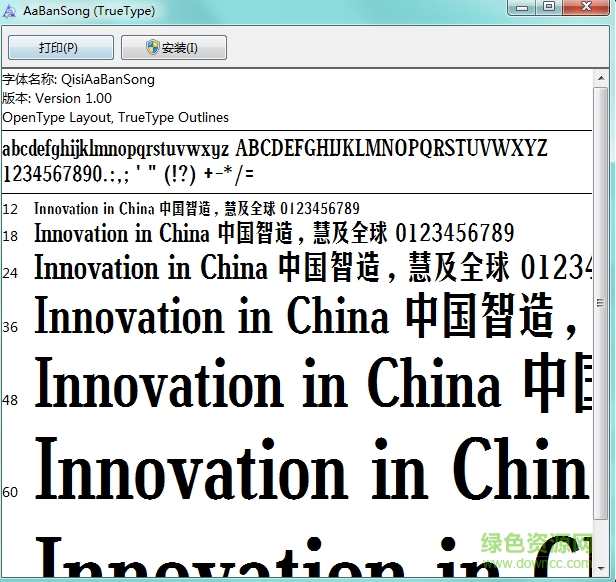
字體管家版宋是一款字跡深沉大氣的版宋體,造型筆直細長,經(jīng)過加黑加粗處理,比一般的字體更加顯眼初中,喜歡的朋友不妨來綠色資源網(wǎng)下載吧!
字體管家版宋共有8465個字符,是字體管家推出的新字體,繼承了宋體纖秀靈活的美感,更拉長了字體的構造,顯得更加深刻,如印版作品。
宋體字是宋朝發(fā)明的一種漢字印刷字體。框架結構象黑體,筆劃橫平豎直,且有粗細變化:橫細豎粗,橫劃末端有裝飾三角形,豎劃、撇劃、鉤劃(橫、豎、撇、彎鉤)、利刀等,開端也有裝飾三角形。宋體字常見有兩種類型:1豐滿型:帶有較明顯的黑體特征,但不象黑體那樣嚴肅莊重。方點(出筆尖收筆方)、撇捺、鉤等筆劃比較豐肥,給人以飽滿、厚重之感;2瘦勁型:圓點(象水滴造型)、撇捺、鉤等筆劃比較瘦勁,給人清秀之感。宋體字字型一般為方型,根據(jù)內(nèi)容和版面需要可以適當壓扁和拉長,以求活潑輕快之感。筆劃的粗細也可以做適當調(diào)整。